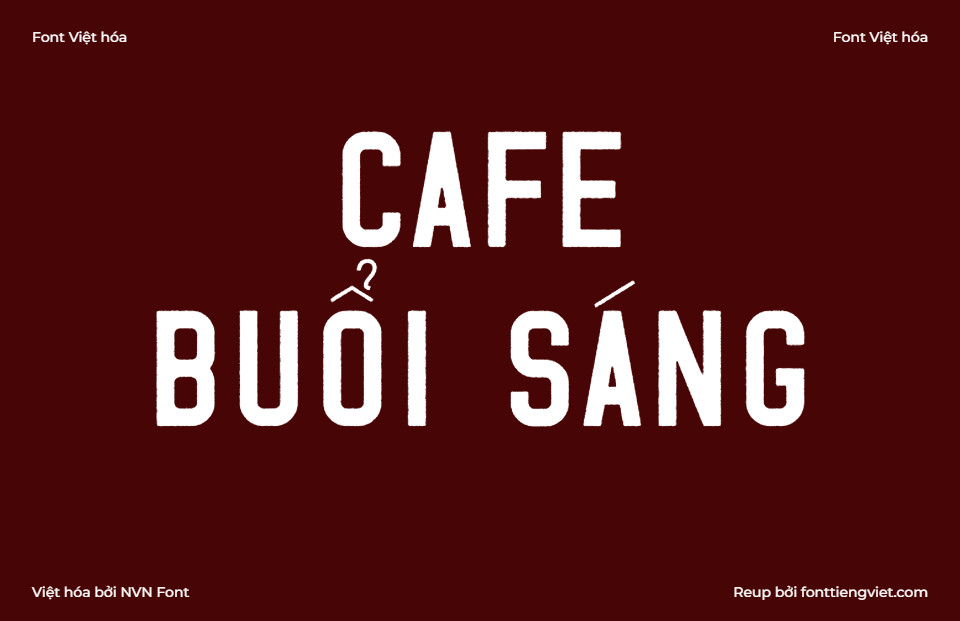
Font Việt hoá NVN Southland Distort Regular
Giới thiệu về Font Việt hoá NVN Southland Distort Regular
Trong thế giới đồ họa hiện đại, việc tìm kiếm một bộ chữ vừa mang tính nghệ thuật vừa đảm bảo khả năng hiển thị tiếng Việt hoàn hảo là điều không hề dễ dàng. Font Việt hoá NVN Southland Distort Regular xuất hiện như một giải pháp cứu cánh cho những nhà thiết kế đang tìm kiếm sự đột phá. Đây là một phiên bản đặc biệt thuộc bộ sưu tập Font Miễn Phí dành riêng cho cộng đồng sáng tạo tại Việt Nam. Với phong cách thiết kế thô mộc, có chút nổi loạn và bụi bặm, font chữ này giúp các tác phẩm của bạn trở nên sống động và có chiều sâu hơn bao giờ hết. Điểm đặc trưng nhất của Southland Distort Regular chính là những nét chữ được làm biến dạng một cách nghệ thuật, tạo cảm giác như được in ấn thủ công trên các bề mặt giấy cũ hoặc vải canvas, mang lại hơi thở của phong cách Vintage và Grunge đầy lôi cuốn.
Đặc điểm nổi bật của Font Việt hoá NVN Southland Distort Regular
Thiết kế độc đáo và tính ứng dụng cao
Bộ Font Việt hoá NVN Southland Distort Regular không chỉ đơn thuần là một kiểu chữ, mà còn là một công cụ truyền tải cảm xúc mạnh mẽ. Các ký tự được tinh chỉnh tỉ mỉ để phù hợp với quy tắc dấu câu trong tiếng Việt, giúp người dùng không còn lo lắng về lỗi hiển thị hay mất dấu khi gõ văn bản. Với độ dày nét vừa phải cùng hiệu ứng “distort” (biến dạng) tự nhiên, nó cực kỳ phù hợp cho các dự án thiết kế bìa sách, poster phim, bao bì sản phẩm thủ công hoặc các tiêu đề video ca nhạc mang phong cách Rock, Indie. Sự kết hợp giữa nét chữ truyền thống và phong cách hiện đại giúp bộ font này dễ dàng chinh phục được cả những khách hàng khó tính nhất.
Tối ưu hóa cho trải nghiệm người dùng
Lưu ý khi sử dụng Font Việt hoá NVN Southland Distort Regular
Dù mang phong cách biến dạng, nhưng bộ font này vẫn đảm bảo tính dễ đọc nếu bạn biết cách sắp xếp khoảng cách chữ (kerning) hợp lý. Bạn nên sử dụng nó cho các đoạn văn bản ngắn, tiêu đề lớn hoặc các câu slogan để phát huy tối đa hiệu ứng thị giác. Tránh dùng cho các đoạn văn bản dài vì đặc tính “distort” có thể gây mỏi mắt nếu trình bày ở kích thước quá nhỏ. Ngoài ra, việc kết hợp bộ chữ này với các tông màu trầm, màu trung tính sẽ giúp tôn lên vẻ đẹp cổ điển và mạnh mẽ vốn có của nó.
Kết luận về bộ font chữ độc đáo